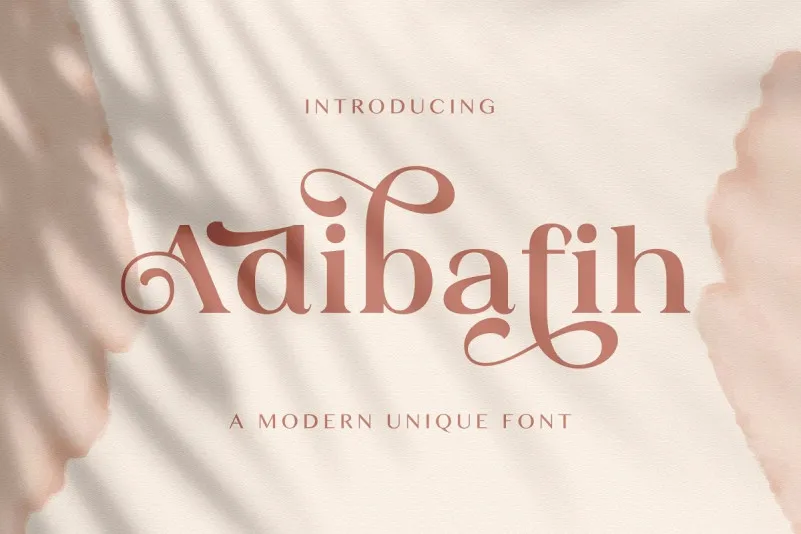
A Adibafih Font é uma elegante serif que traz nuances a qualquer projeto, sem perder sua simplicidade. Seu caráter único proporciona uma combinação perfeita de beleza e delicadeza. Ela se encaixa facilmente em um grande número de projetos, tornando-a uma excelente opção para designers buscando dar uma nova perspectiva aos seus trabalhos. Experimente Adibafih e veja como ele pode transformar sua visão criativa. Perfectamente adaptada a um rango amplo de ideias gráficas, ela é capaz de destacar seu design. Não perca tempo, adquira Adibafih hoje e venha explorar o poder de uma fonte que vai além do básico.